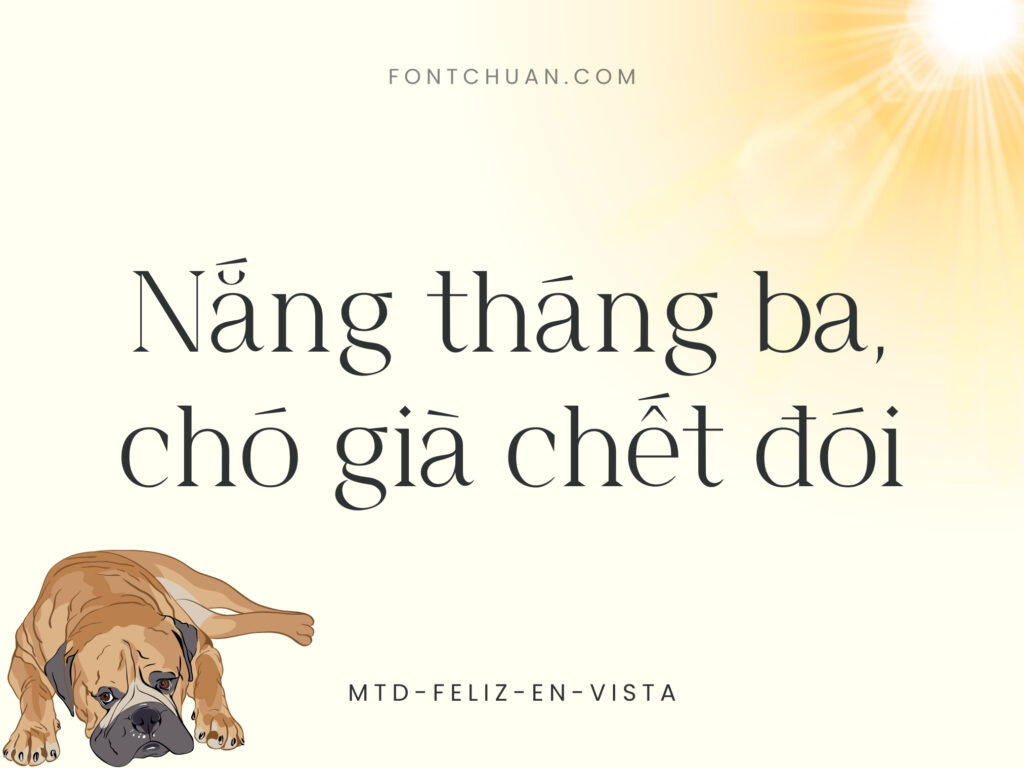
Font MTD Feliz En Vista là một phông chữ serif hiện đại, được thiết kế bởi Harmonais Visual và phát hành trên trang web chính thức của họ. Font đã được Việt hóa bởi Mộc Hạ, hỗ trợ tiếng Việt và hơn 90 ngôn ngữ khác, giúp mở rộng khả năng ứng dụng trong các thiết kế đa ngôn ngữ. Đây là một trong những phông chữ được cộng đồng thiết kế đánh giá cao và ứng dụng trong nhiều dự án sáng tạo, đáp ứng nhu cầu đa dạng của người dùng.
MTD Feliz En Vista nổi bật với các chữ in hoa đẹp mắt và một chút giao diện thời trang, mang đến cảm giác sang trọng và hiện đại. Font rất phù hợp cho các thiết kế logo, tiêu đề tạp chí, thương hiệu thời trang, thiệp mời và các ấn phẩm đòi hỏi sự tinh tế và chuyên nghiệp. Các ngành nghề phù hợp bao gồm quảng cáo, giáo dục, công nghệ, thiệp cưới và ảnh cưới. Font này cũng lý tưởng cho các sự kiện như Tết, Giáng sinh, Valentine và các lễ hội khác.